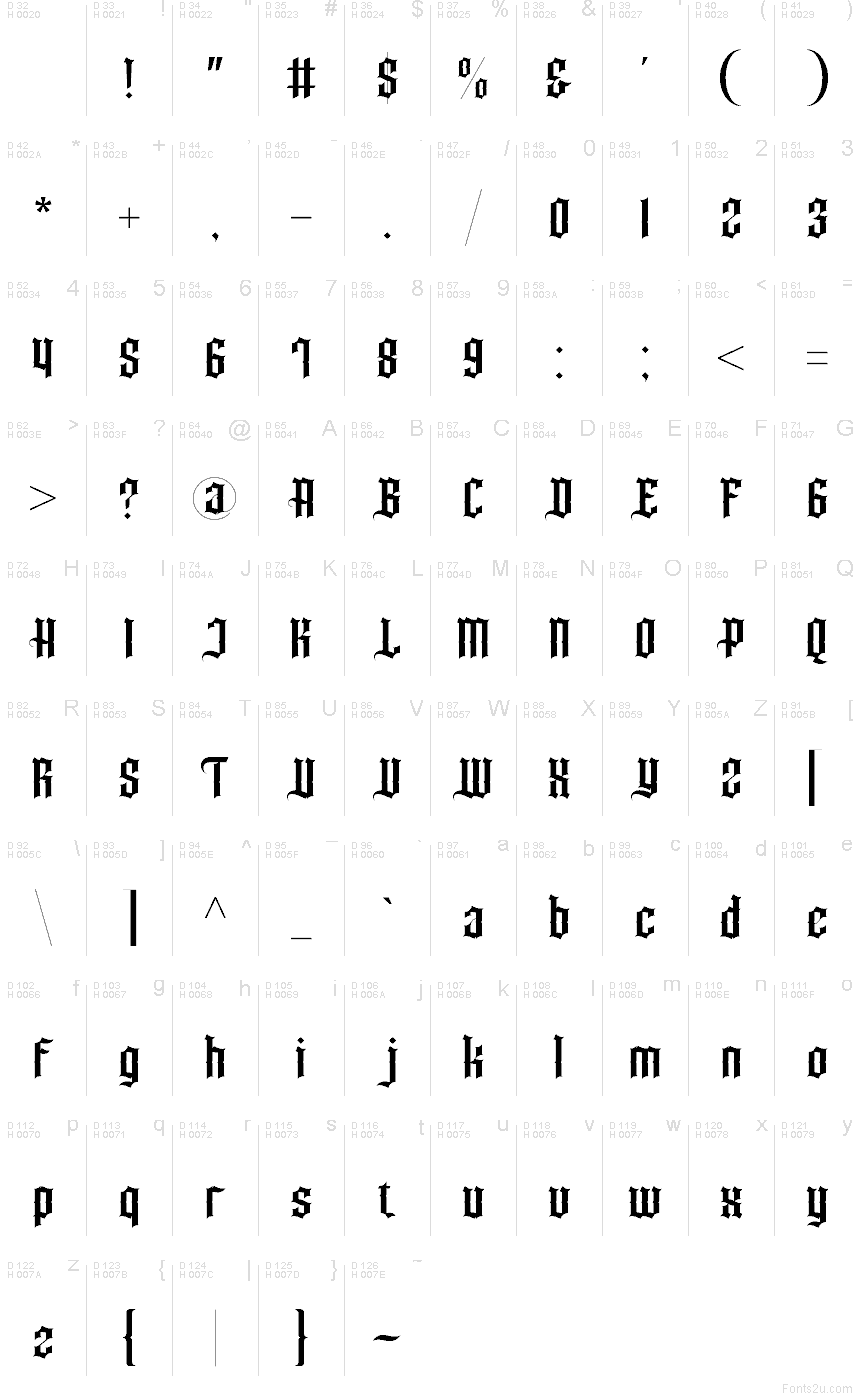
Maknin
Maknin od Ermedia Studio je bezplatné stredoveké lomené písmo s vysokými, tesne zovretými tvarmi a výrazným kontrastom medzi hrubými a tenkými ťahmi. Rozštiepené zakončenia pripomínajúce čepele a široké zakrivené ozdoby dodávajú nápisom ceremoniálny ráz.
Jeho špicaté siluety pripomínajú heraldické erby a ryté ornamenty, vďaka čomu je písmo užitočné pri grafike fantasy hier aj plagátoch historických podujatí. Tvary sa hodia aj na obaly metalových albumov. Pri propagačných predmetoch a tematických obaloch spájajú tie isté temné, formálne detaily toto písmo so stredovekým ceremoniálom a gotickou hudobnou kultúrou.